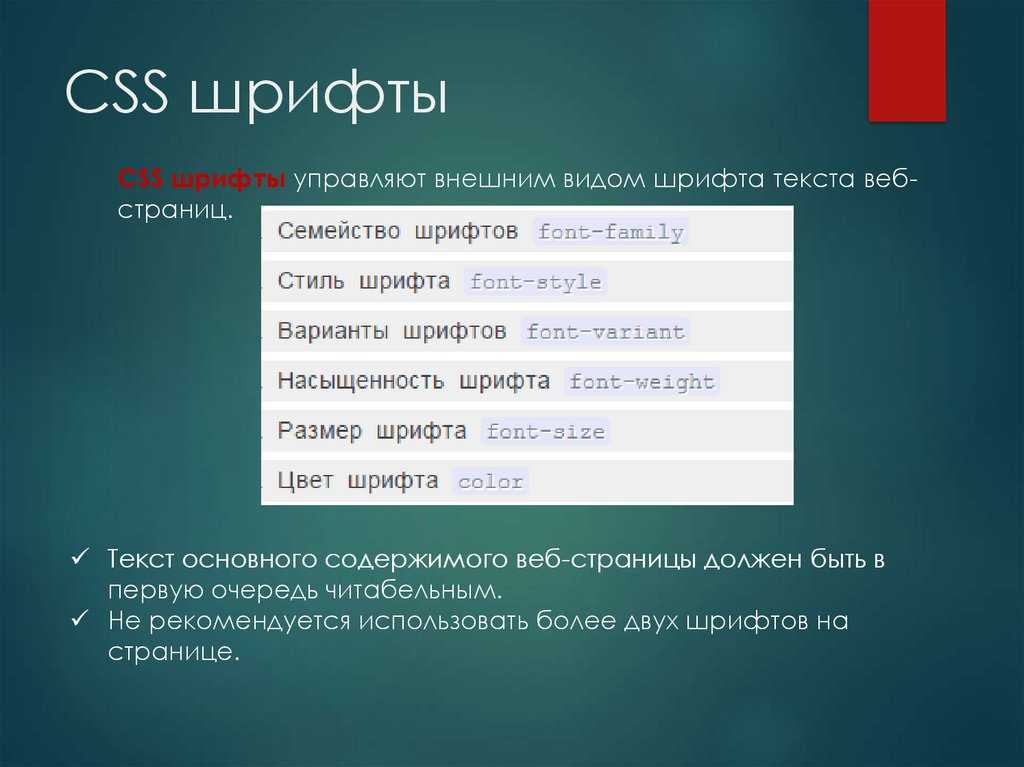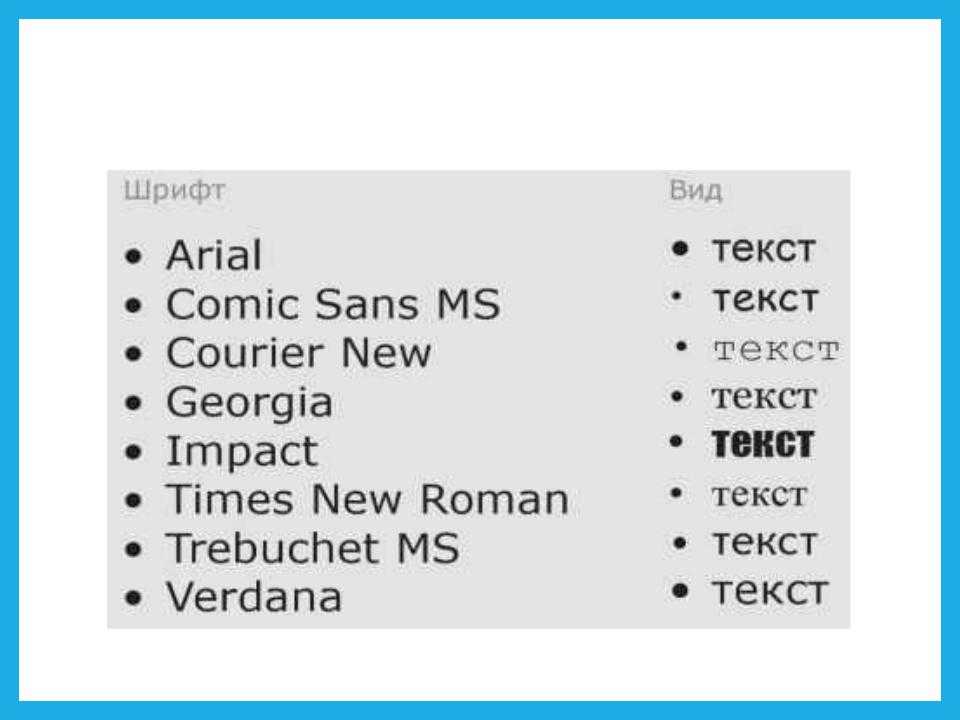
| Название шрифта | Win 2000 | Win XP | Vista | Win 7 | Win 8 |
| Arial | + | + | + | + | + |
| Arial Black | + | + | + | + | + |
| Book Antiqua | + | ||||
| Calibri | + | + | + | ||
| Cambria | + | + | + | ||
| Candara | + | + | + | ||
| Comic Sans MS | + | + | + | + | + |
| Consolas | + | + | + | ||
| Constantia | + | + | + | ||
| Corbel | + | + | + | ||
| Courier | + | + | + | + | + |
| Courier New | + | + | + | + | + |
| Estrangelo Edessa | + | + | + | + | |
| Franklin Gothic Medium | + | + | + | + | |
| Gautami | + | + | + | + | |
| Gabriola | + | + | |||
| Georgia | + | + | + | + | + |
| Georgia Italic Impact | + | ||||
| Impact | + | + | + | + | + |
| Latha | + | + | + | + | |
| Lucida Console | + | + | + | + | + |
| Lucida Sans Console | + | + | + | + | |
| Lucida Sans Unicode | + | + | + | + | + |
| Marlett | + | + | + | + | + |
| Modern | + | + | |||
| Modern MS Sans Serif | + | ||||
| MS Sans Serif | + | + | + | + | + |
| MS Serif | + | + | + | + | + |
| MV Boli | + | + | + | + | |
| Nyala | + | + | + | ||
| Palatino Linotype | + | + | + | + | + |
| Roman | + | + | + | + | + |
| Script | + | + | + | + | + |
| Segoe Print | + | + | + | ||
| Segoe Script | + | + | + | ||
| Segoe UI | + | + | + | ||
| Small Fonts | + | + | |||
| Symbol | + | + | + | + | + |
| Tahoma | + | + | + | + | + |
| Tempus Sans ITC | + | ||||
| Times New Roman | + | + | + | + | + |
| Trebuchet MS | + | + | + | + | + |
| Tunga | + | + | + | + | |
| Verdana | + | + | + | + | + |
| Webdings | + | + | + | + | + |
| Westminster | + | ||||
| Wingdings | + | + | + | + | + |
Рекомендуется прописывать шрифт в CSS, сгруппировав сразу 3-4 похожих шрифта на случай отсутствия основного из них у конечного пользователя.
Пример: font-family: Webdings, Garamond, Times New Roman, Sans;
Ниже приведен список стандартных шрифтов для операционной системы Microsoft Windows и MacOS X Apple. В таблице использованы группы стандартных шрифтов Windows и Mac для безопасного использования во всех браузерах.
1 Шрифты Georgia и Trebuchet MS поставляются вместе с Windows 2000/XP и включены в пакет шрифтов IE, поэтому они установлены на многих компьютерах с ОС Windows 98.
2 Символьные шрифты отображаются только в Internet Explorer, в остальных браузерах они обычно заменяются на стандартный шрифт (хотя, например, шрифт Symbol отображается в Opera, а Webdings — в Safari).
3 Шрифт Book Antiqua практически идентичен Palatino Linotype, который поставляется с Windows 2000/XP, а Book Antiqua — с Windows 98.
4 Обратите внимание, что эти шрифты не TrueType, а bitmap, поэтому они могут отображаться с пикселизацией в крупных размерах.
Эти шрифты предназначены для отображения в размерах 8, 10, 12, 14, 18 и 24 pt при 96 DPI).
5 Эти шрифты работают в Safari только в стандартном начертании и не работают при выделении жирным или курсивом. Comic Sans MS также используется жирным выделением, но не курсивом. Другие Mac-браузеры самостоятельно эмулируют отсутствующие у шрифтов свойства.
6 Эти шрифты устанавливаются в Mac только при Classic-инсталляции.
Windows Vista, Internet Explorer 7, ClearType включен:
Windows Vista, Firefox 2.0, ClearType включен:
Mac OS X 10.4.8, Firefox 2.0, ClearType включен:
В html размер шрифта играет важную роль. Он позволяет обратить внимание пользователя на важную информацию, размещенную на странице сайта. Хотя важен не только размер букв, но и их цвет, толщина и даже семейство.
Теги и атрибуты при роботе со шрифтами html
Возможности атрибута style
2) font-size – задается размер от 1 до 7.
Это один из основных способов того, как в html можно увеличить шрифт.
Синтаксис написания:
Размер шрифта можно также задать:
Пример того, как поменять шрифт в html с помощью этого свойства:
Пример того, как изменить шрифт в html этим свойством:
Свойство font и цвет шрифта html
Font является еще одним контейнерным свойством. Внутри себя оно объединило значения нескольких свойств, предназначенных для изменения шрифтов. Синтаксис font :
Также в качестве значения могут быть заданы шрифты, используемые системой в надписях на различных элементах управления:
Русскоязычные шрифты и их поддержка
Не все из установленных в операционных системах шрифтов поддерживают русскую раскладку. Поэтому в веб-разработке лучше всего применять семейства шрифтов, проверенные на практике. Вот шрифты для html русские:
- Windows XP, Firefox 1.0.7, ClearType включен
- Windows XP, Internet Explorer 6, базовое сглаживание шрифтов включено
- Windows XP, Firefox 1.0.7, базовое сглаживание шрифтов включено
- Windows 2000, Internet Explorer 6, базовое сглаживание шрифтов включено
- Windows 2000, Firefox 1.
«Bold» соответствует весовому значению «700», Heavy — «800», Black — «900».
Например, буква «I» будет намного уже, чем «W». В CSS — моноширинный шрифт выбирается или с помощью конструкции font-family: monospace, и/или указанием названия конкретного моно-шрифта. Например: